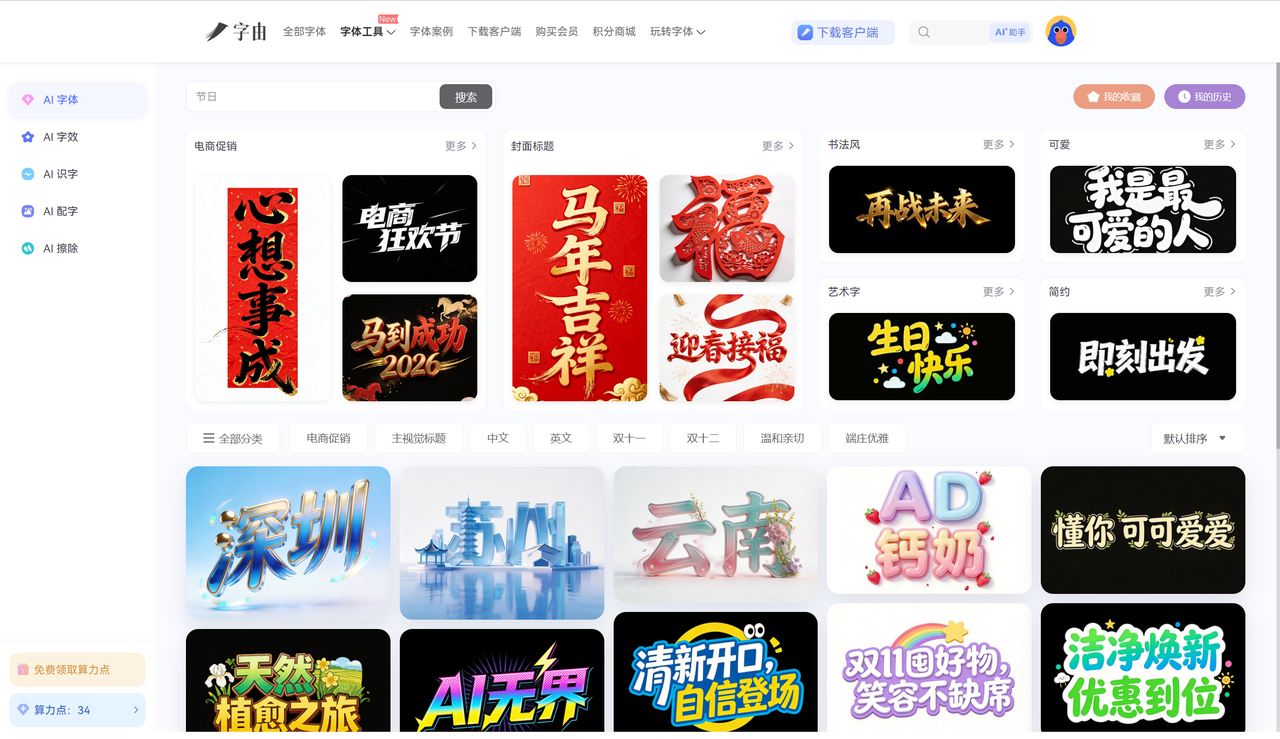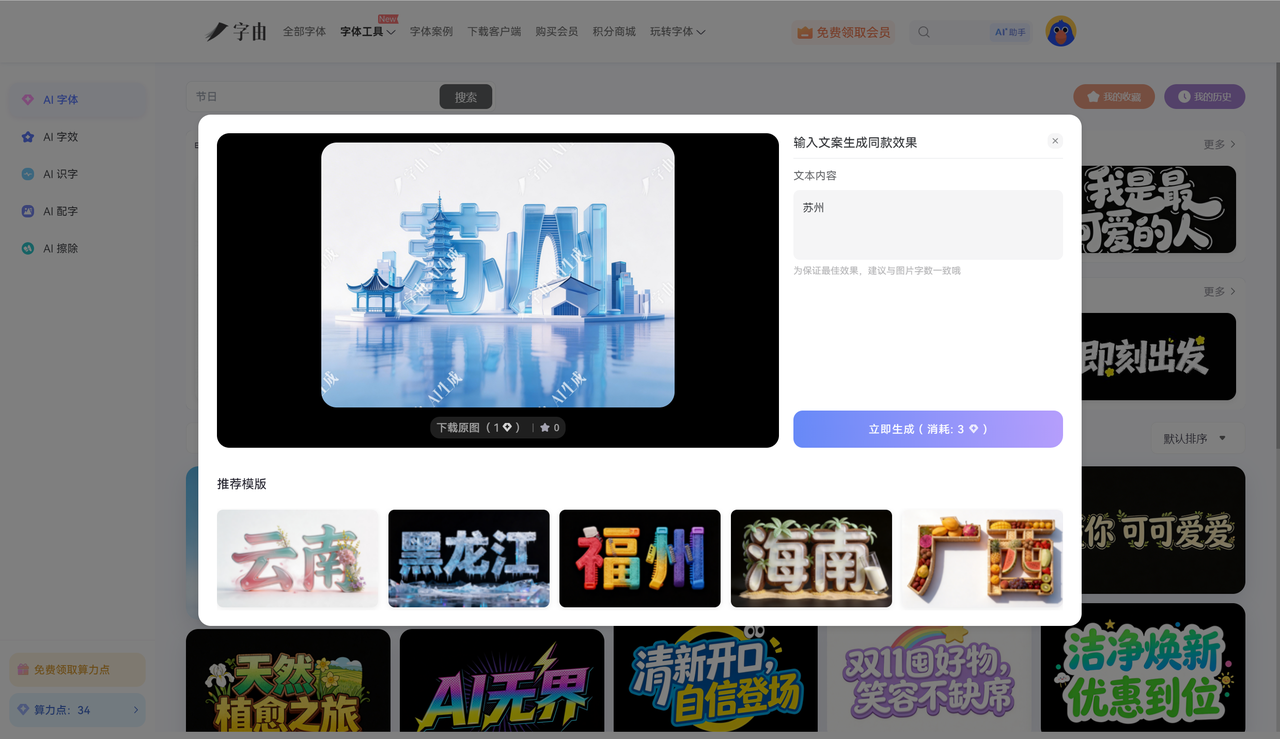
做海报缺艺术字?试试这几个PS艺术字体免费下载网站
做海报最头疼的是什么?构图想好了,配色选好了,图片也修好了,结果卡在标题字上。电脑自带的字体大部分其实都不太适合那种有主题的海报设计,就算用的话也会显得画面很死板,如果再搜索字体推荐帖子,再在帖子里找合适的网站,一套流程下来实在是太费时间了,而且就算有字体的话效果也不一定能合自己心意。但是其实这件事根本就没有那么难,今天我就会推荐几个PS艺术字体免费下载网站,从国产神器字由到国外精选平台,每个都能让你快速搞定艺术字。需要的可以收藏,以后再找不迷路。
很多人所知的字由是一个字体库,事实确实是这样,但是大家可能还不知道字由其实相当于一个字体工具箱,里面还有更多关于字体的工具,每一个都十分使用。其中的AI字体功能,才是做艺术字的“捷径”。你不需要去网上搜字体、下载、安装、重启PS,直接在字由里选个模板,输入文字,生成艺术字,然后拖进PS里用。整个过程都在线完成,和PS无缝衔接。接下来我就会详细介绍怎么使用字由的AI工具生成艺术字:
- 第一步:打开字由客户端,进入【AI字体】。在搜索框里输入你想要的风格,比如“艺术”“创意”“海报标题”,系统会筛出一堆艺术字模板。每个模板都是现成的设计——带特效、带配色、带背景,你不需要自己调任何参数
- 第二步:选一个顺眼的模板,点“做同款”,把模板里的文字换成你的标题(最好和模板字数一样),点“立即生成”,几十秒就能拿到一张透明背景的PNG。下载保存,艺术字就到手了。
- 第三步:生成的艺术字是透明背景的PNG,直接拖进PS里,放到海报上就行。不需要抠图,不需要调色,不需要加效果,模板里都给你做好了。你可以调整位置、大小,也可以继续加其他元素。
另外,字由还有一款AI工具是AI 字效,如果你已经有了一款基础字体,想给它加个艺术效果,比如霓虹、金属、水彩,可以用字由的【AI字效】。内置400多种特效模板,点一下就能加,不用自己调图层样式。生成后同样是透明背景PNG,拖进PS里直接用。
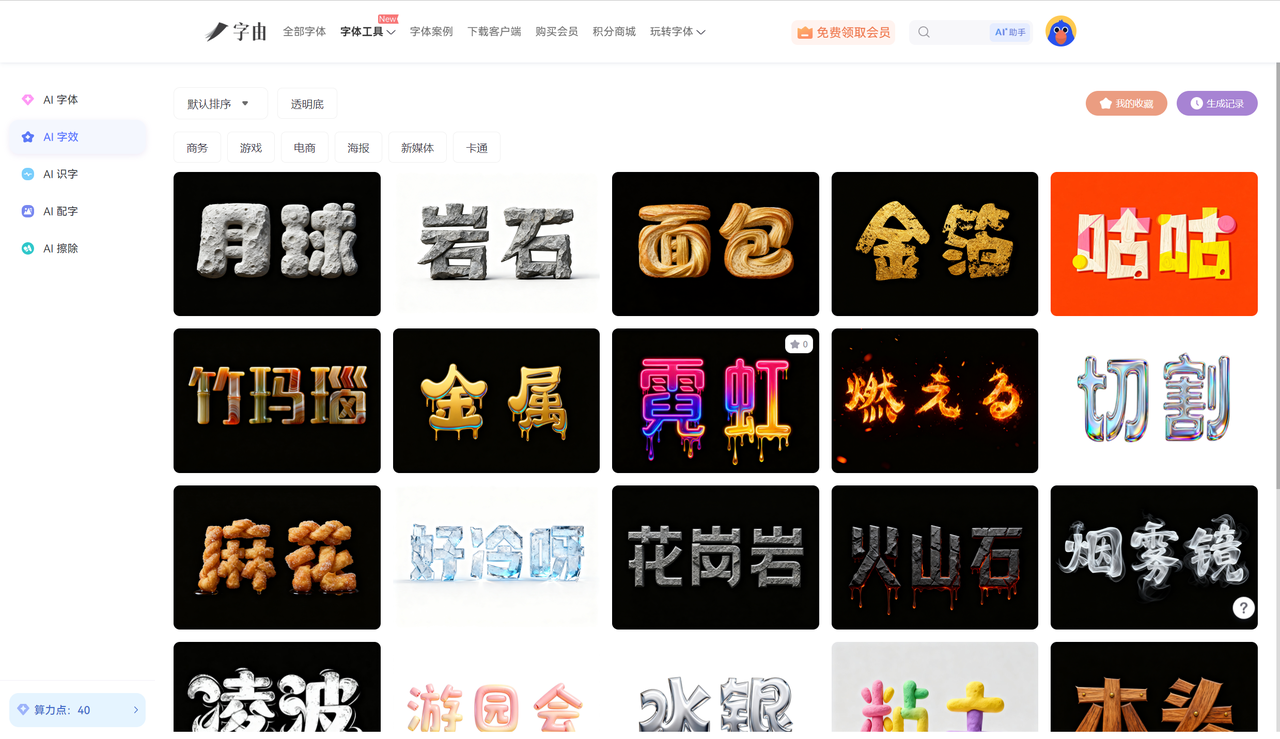
这两个AI工具对于想要快速生成艺术字的设计师来说十分适合,丰富的模板和工具能够快速响应你的需求,最重要的是可以免费使用,其他软件如果想要生成艺术字很有可能要付费,字由则是替我们省了一笔钱。
2、Just Free Fonts
Just Free Fonts 是一个简洁的免费字体网站,它专门有一个“Artistic”分类。从筛选看,这个分类下收录了19款艺术字体,每款都标注了设计师和风格,我比较推荐的有:
- Kleymissky:由Gzegorz Luk设计,1种字重,艺术风格
- Flowmery:由Alit Design设计,1种字重,花卉装饰感
- Smooth Script:由Rob Leuschke设计,1种字重,流畅手写
- Haunting Eleanor:由Typesgal设计,暗黑艺术风格
- Mioq:由med ness设计,抽象几何感
- Hyped:由Sinister Fonts设计,潮流涂鸦风
每款字体都有预览图,可以直接下载使用。如果你需要一些有艺术感但又不太夸张的字体,这里是个比较好的选择,虽然字体效果方面不如字由突出但是好在字体的普适性很强,就算后面想拿来做艺术效果也是不错的底层字体参考。
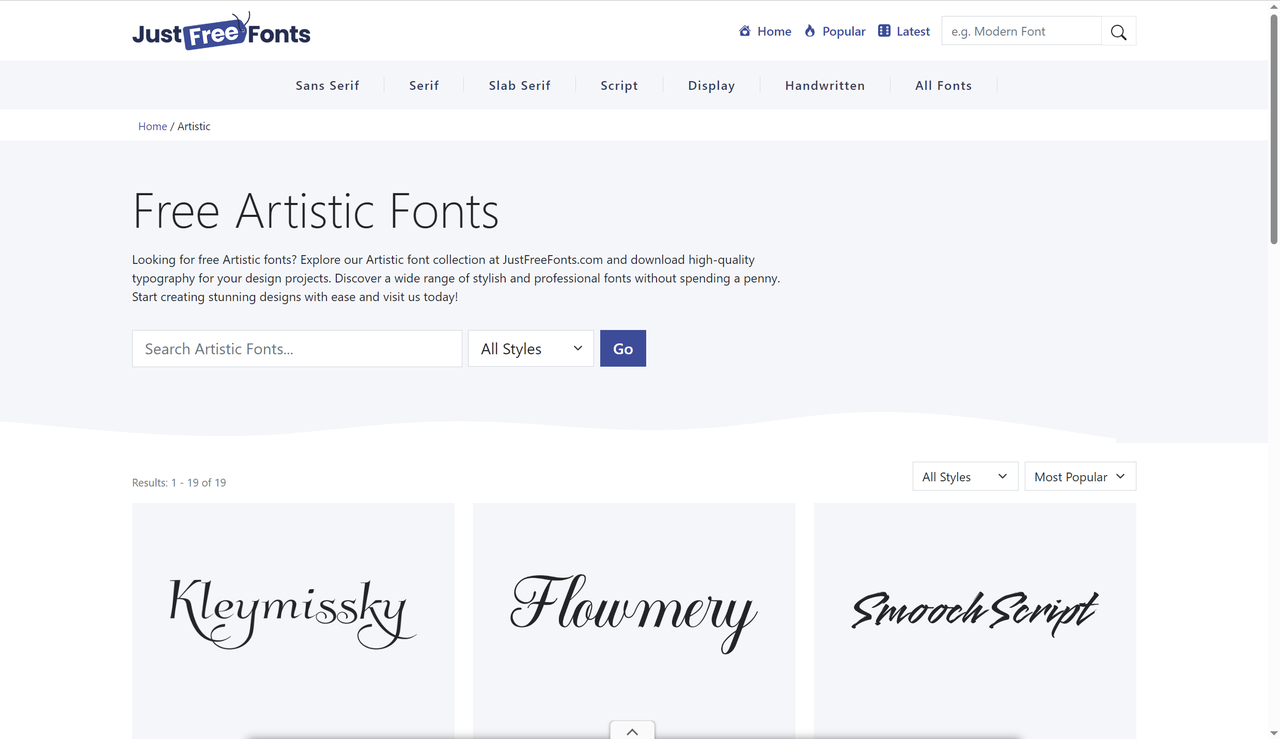
3、FONNTS
这个网站专门介绍艺术字体,从主页的标题语可以看出,它把艺术字体定义为“以其富有表现力和想象力的设计而闻名”。它推荐了几款艺术字体,并提供了详细的分类筛选,我比较推荐的两款字体有:
- Ut Forsaken Village:2种字重,暗黑哥特风
- Tiki Tropical:3种字重,热带岛屿风格
网站还提供了“Quick Try”功能,可以快速预览字体效果。如果你对艺术字体的设计理念感兴趣,这里能帮你了解什么样的字体才算“艺术”。
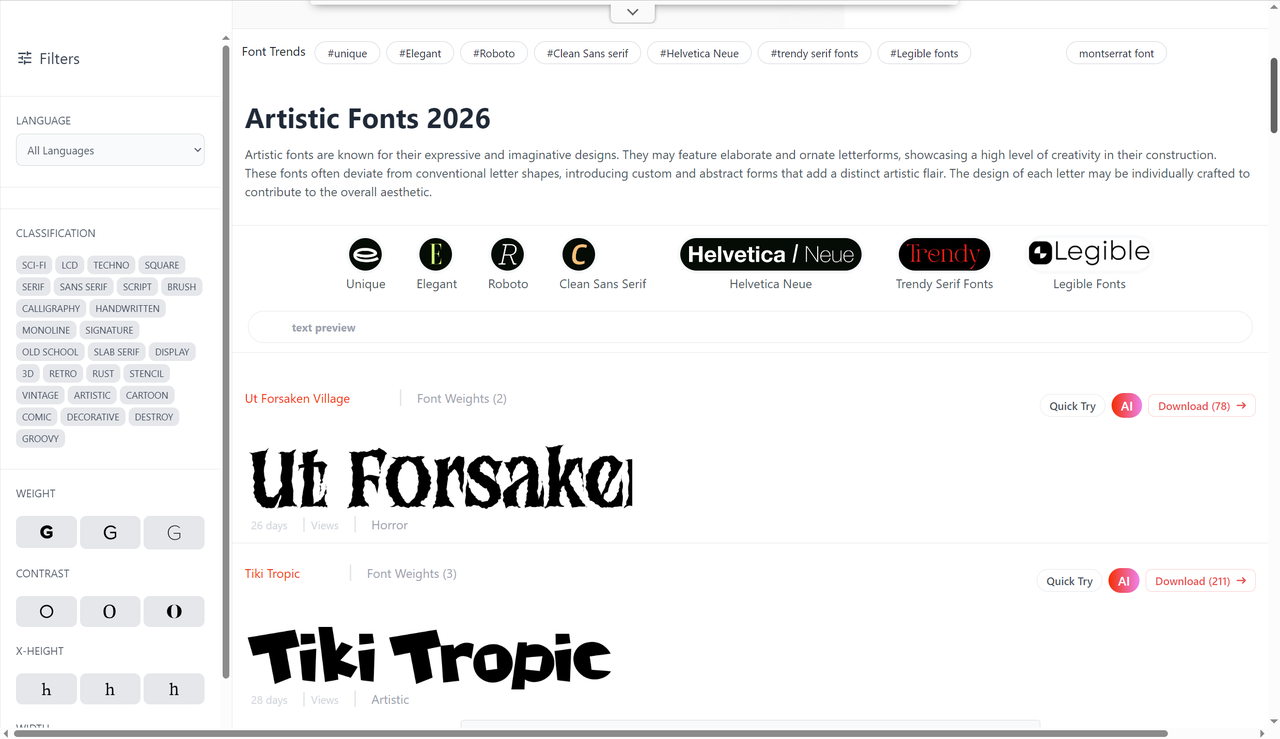
4、1001 Free Fonts
1001 Free Fonts 是一个老牌字体网站,它的“Artistic Fonts”分类收录了886款字体。从主页面我们可以看到,它的相关风格标签非常丰富:artistic、bold、title、headline、script、handwriting、handwritten、calligraphy、stylish、expressive、modern、logotype、diy……
推荐几款示例字体:
- Rustic Roadway:乡村复古风,标注“Personal use”
- Priestacy:神秘宗教风格
- Rockybilly:摇滚复古风
- Moralana:优雅花体
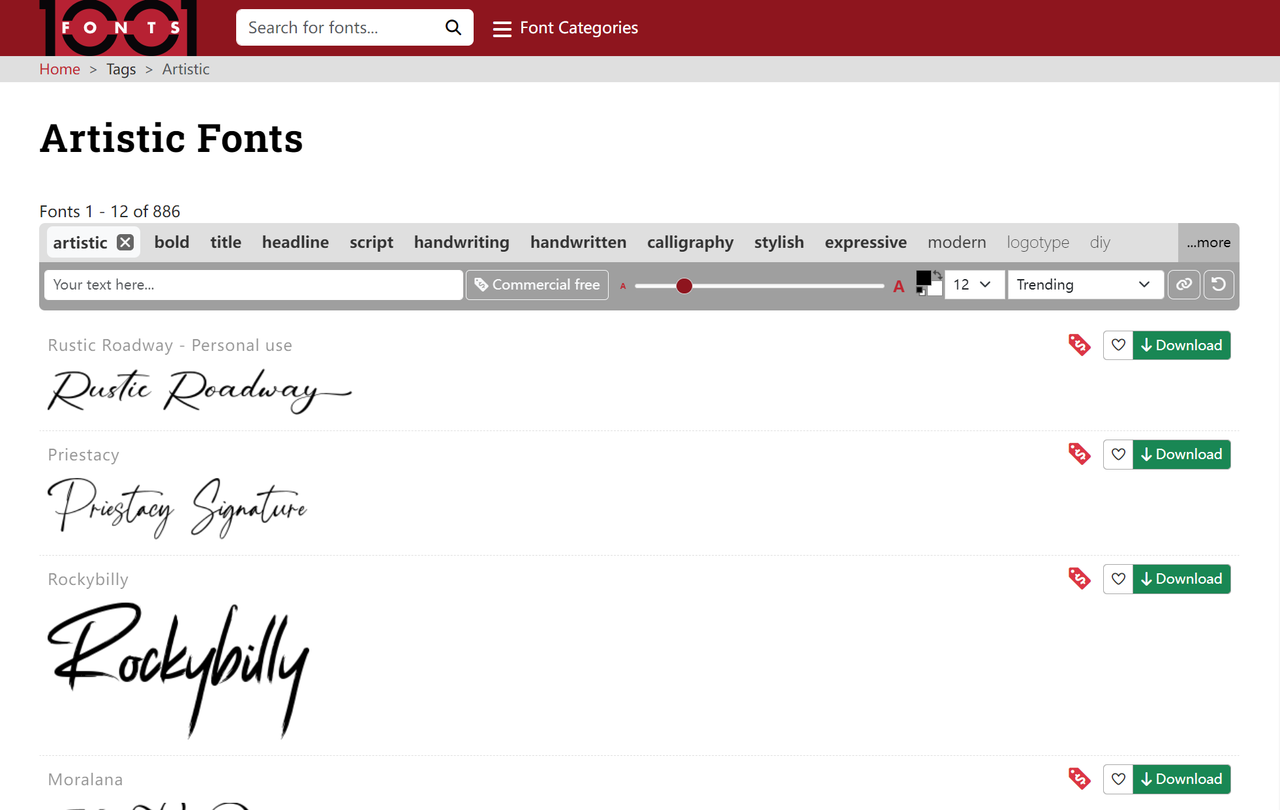
有时候做海报不是缺字体,问题在于没有找到合适的字体网站,这4 个PS艺术字体免费下载网站,有人喜欢Just Free Fonts的精选,有人偏爱艺术字体站的设计理念,有人需要1001 Free Fonts的海量资源。而字由对我来说,是那个把“生成”和“使用”结合得最好的选择,它让你不用下载安装,直接在AI字体里生成艺术字,拖进PS里就能用。如果你也想让海报标题更出彩,不妨从字由开始试试。